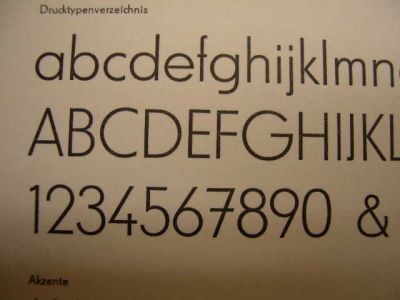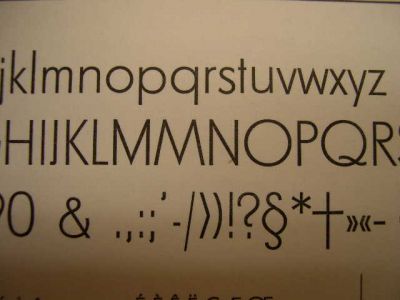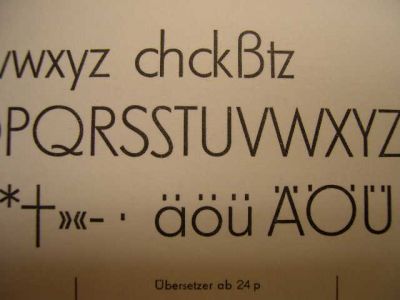
Berthold-Grotesk
H.Berthold AG, Berlin
Erstguß 1928
Hausschnitt
Laß Dich nicht durch das Rund-a verwirren. Die Berthold hatte unterschiedliche Versionen und in meinem Schriftmuster unten ist das runde gemeine "a" nicht dabei. Die Ziffer "7" hat vorn einen kleinen Abstrich nach unten, richtig?
Futura
Edit: Korrigiere, zumindest ist es nicht die Futura die ich hier vorliegen habe. Das M ist z.B. anders.
Berthold Grotesk für OSRAM sehe ich auch so.
NARVA = DDR-OSRAM-Nachfolger.
Möglicherweise wurde dafür die Super Grotesk verwendet?
BGW und IKA sagen mir jetzt zwar nix, könnten aber auch DDR-Marken sein. Mal auf die Eins achten.
Ich hab's. Wir hatten beide unrecht, die Muster sind aber auch recht klein. Dein Hinweis mit OSRAM - NARVA hat mich darauf gebracht.
Es ist die Fundamental-Grotesk
Ludwig Wagner, Leipzig
Erstguß 1939
Prof. Arno Drescher
Man erkennt es eindeutig an den Querstrichen in der Ziffer 7.
Die Fundamental wurde von TypoArt dann weiterbetrieben.
Aber es gibt keine andere Grotesk, in der die 7 einen Querstrich hat.
Vielleicht sind die Seiten unterschiedlich gesetzt?
In 1949 war noch sehr viel kaputt. Ich habe mal in einer alten Fachzeitschrift gelesen, daß die Druckereibesitzer oft mit der Schaufel in den zerbombten Druckereien die Bleiplacken zusammengekratzt haben, um was zum Gießen für ihren Maschinensatz zu haben. Sicher waren auch die Matrizenbestände zum großen Teil zerstört.